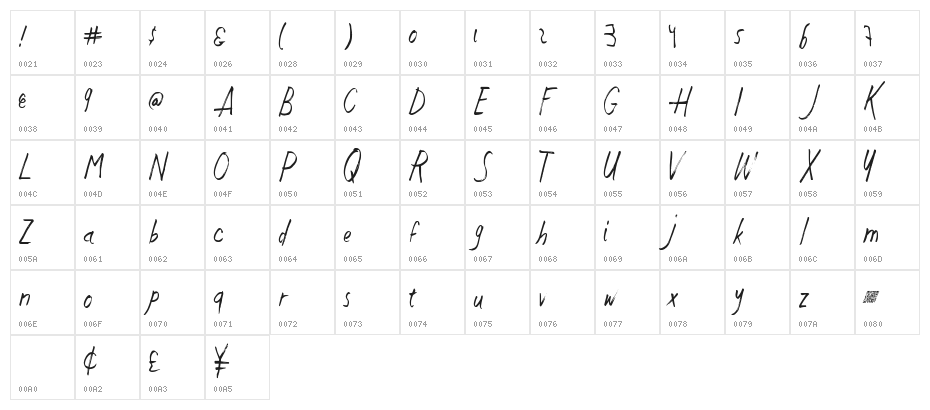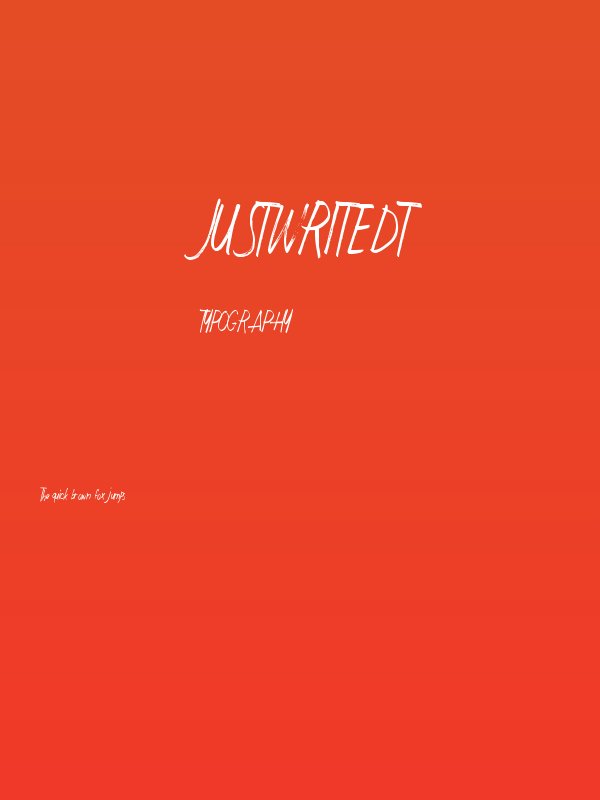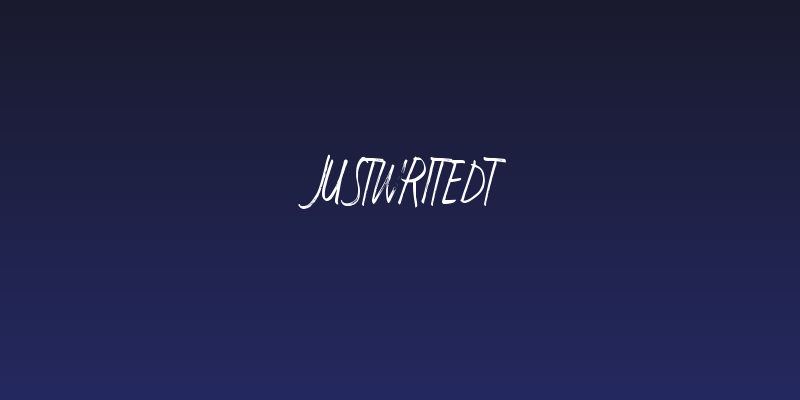
JustWriteDT Font
| Estilo general | Expressive, Artistic |
| Caso de uso | Headlines, Logos, Creative projects |
| Proyectos propuestos | Ideal for creative projects such as greeting cards, invitations, posters, and branding materials that require a personal and artistic touch. |